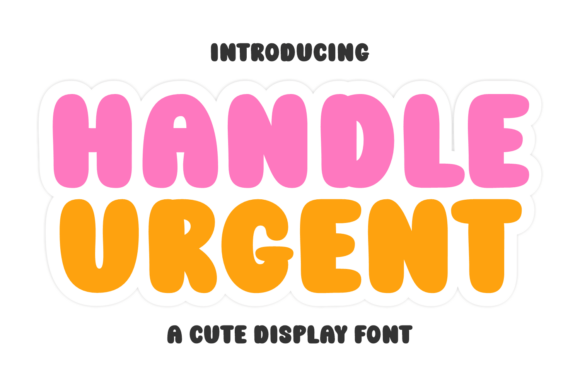
Handle Urgent
إذا كنت تبحث عن أصول عالية الجودة مثل Handle Urgent، فإن هذه الحزمة المميزة هي خيار رائع لمشاريعك الإبداعية.
سواء كنت تقوم بإنشاء منتجات الطباعة عند الطلب أو دعوات الزفاف أو رسومات وسائل التواصل الاجتماعي، فإن Handle Urgent هو الخيار المثالي.